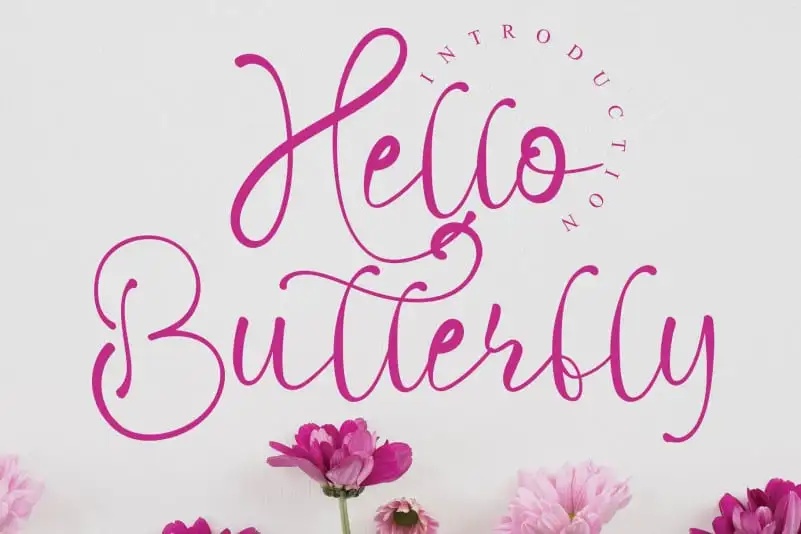
Hello Butterfly Calligraphy Font – Fonte Grátis
Hello Butterfly Calligraphy Font
Aproveite uma experiência única com a ‘Hello Butterfly Calligraphy Font’, perfeita para aqueles que buscam algo mais além na sua escrita. Desenvolvida pelo designer criativo creativeletter, esta fonte oferece um toque especial e único no seu trabalho de escritura artística. Com linhas suaves e formas arredondadas, a ‘Hello Butterfly’ é ideal para trabalhos pessoais ou profissionais que valorizam um estilo elegante e refinado. Ideal tanto para criações digitais quanto impressas, esta fonte permite que você se destaque com uma escrita cheia de personalidade. Seja no design de gráficos, editoriais de moda ou até mesmo em ilustrações de arte, a ‘Hello Butterfly’ traz uma sensação leve e feminina ao seu trabalho. Não hesite em explorar como essa font pode transformar sua escrita artística em algo verdadeiramente especial. Quer mais? Então comece pelo download da fonte! Aqui está uma chance para você personalizar ainda mais o seu espaço de trabalho, com um toque que vai fazer toda a diferença.